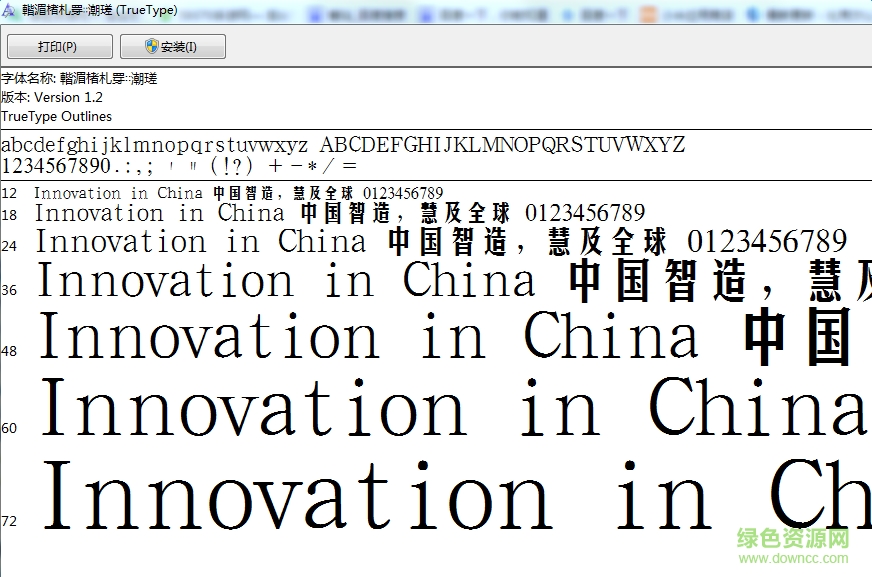
迷你簡長美黑字體是一款迷你字體中文字體,采用簡體打造而成,字體優(yōu)美,是您必備的設(shè)計字體素材,喜歡的親,可以來綠色資源網(wǎng)下載體驗唄!
迷你簡長美黑是一款字形偏長型的中文簡體漢字,婷婷玉立,大方得體,適用于藝術(shù)設(shè)計、廣告設(shè)計、平面設(shè)計、正文標題等領(lǐng)域,喜歡的朋友快下載收藏吧。